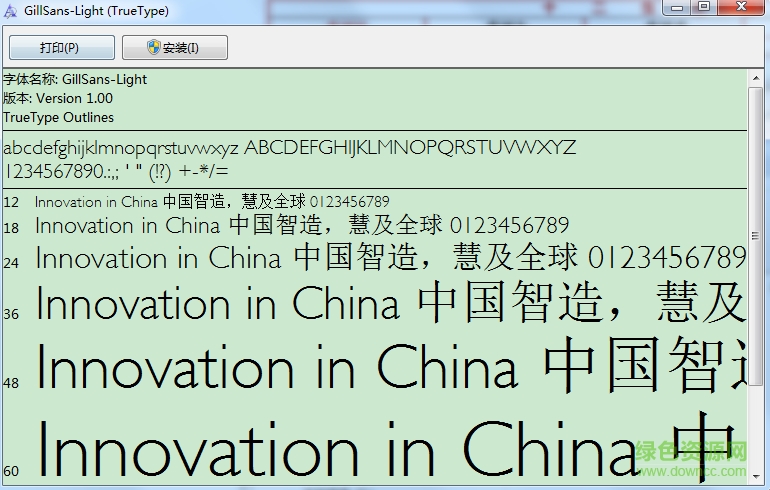
gill sans light是一款非常漂亮的英文字體,這款字體筆觸細(xì)膩,字形簡(jiǎn)潔優(yōu)雅,看起來十分美觀,感興趣的朋友歡迎來本站下載。
gill sans light是一款非常不錯(cuò)的英文字體,這款字體具有非常強(qiáng)的個(gè)性風(fēng)格,適合各類設(shè)計(jì)領(lǐng)域使用,有需要的朋友就趕快來綠色資源網(wǎng)下載!